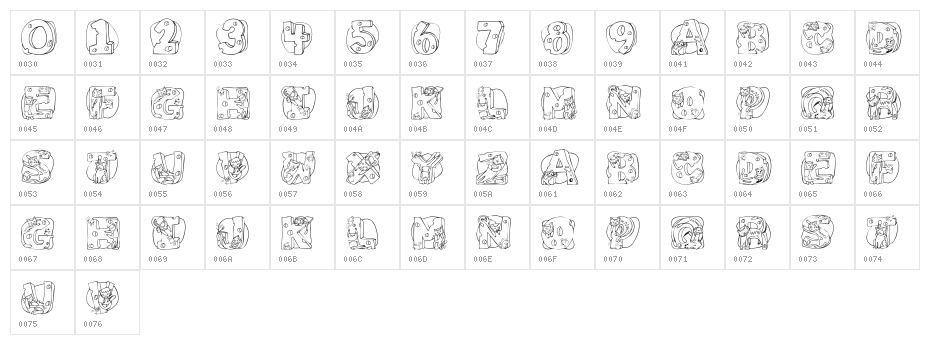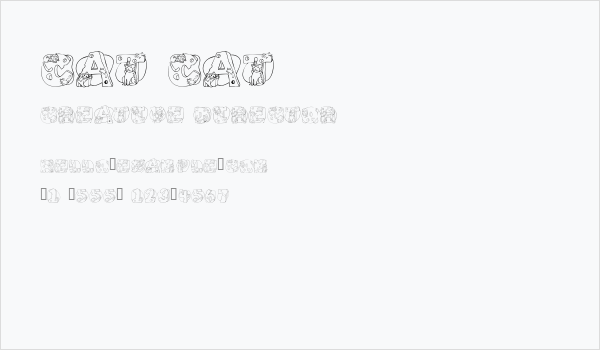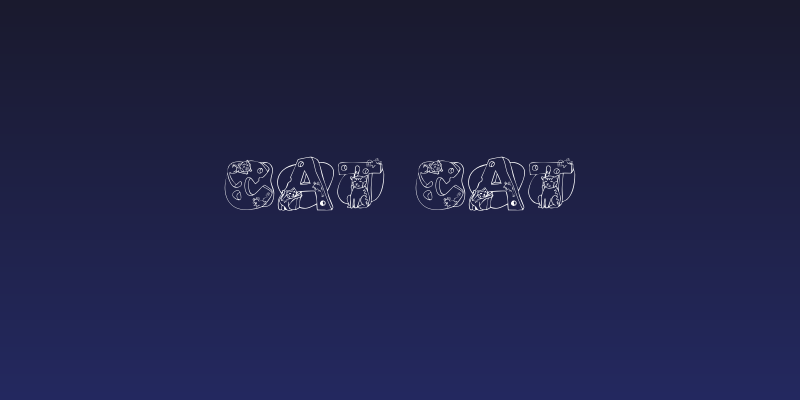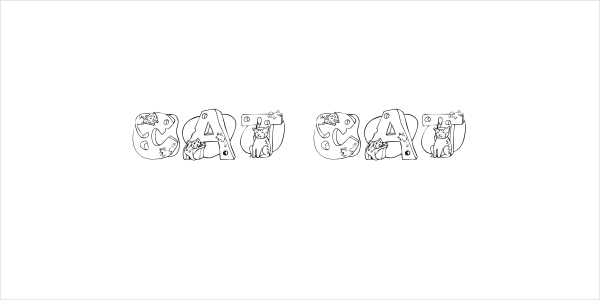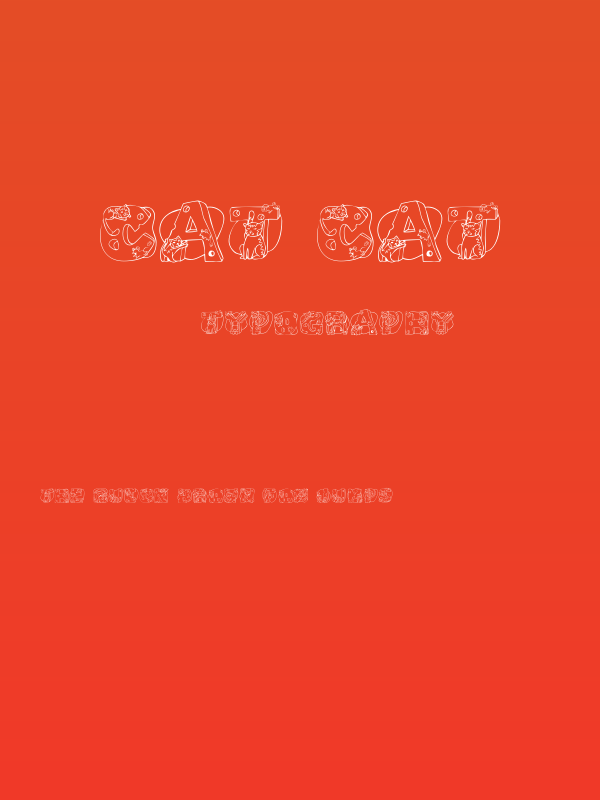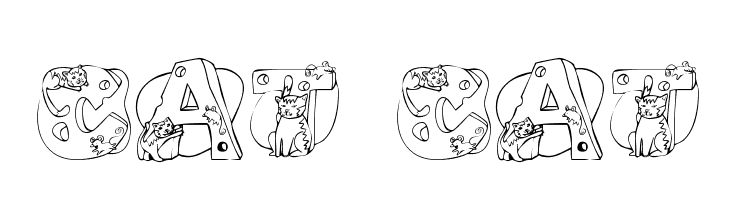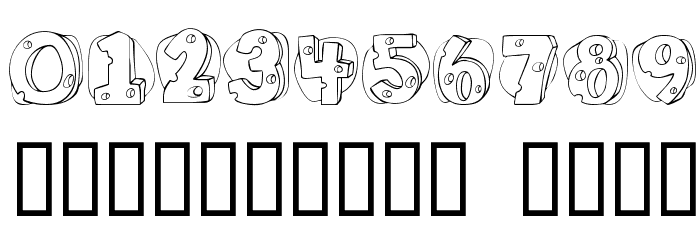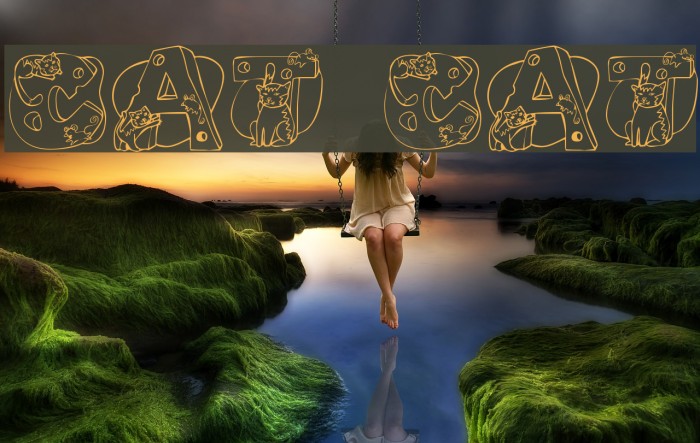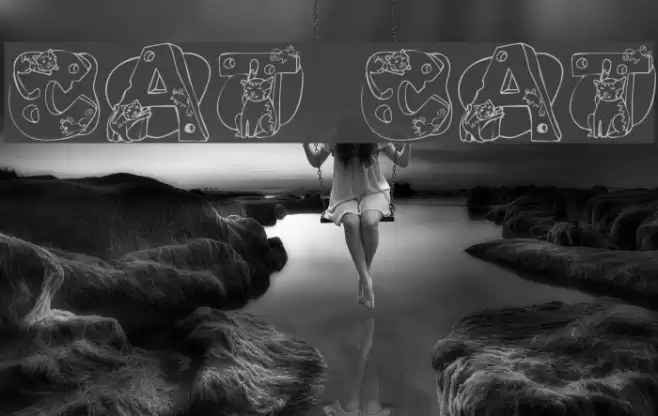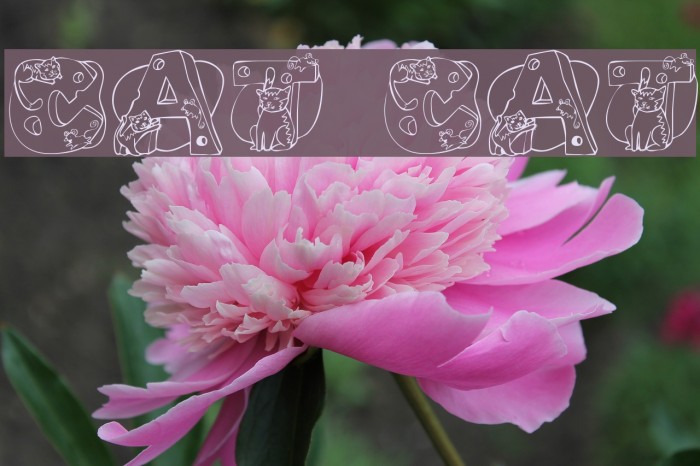
Cat Cat Font
✎ Outline
| النمط العام | Playful, Whimsical |
| مشاريع مقترحة | Ideal for children's books, pet-related branding, playful posters, and novelty items. |